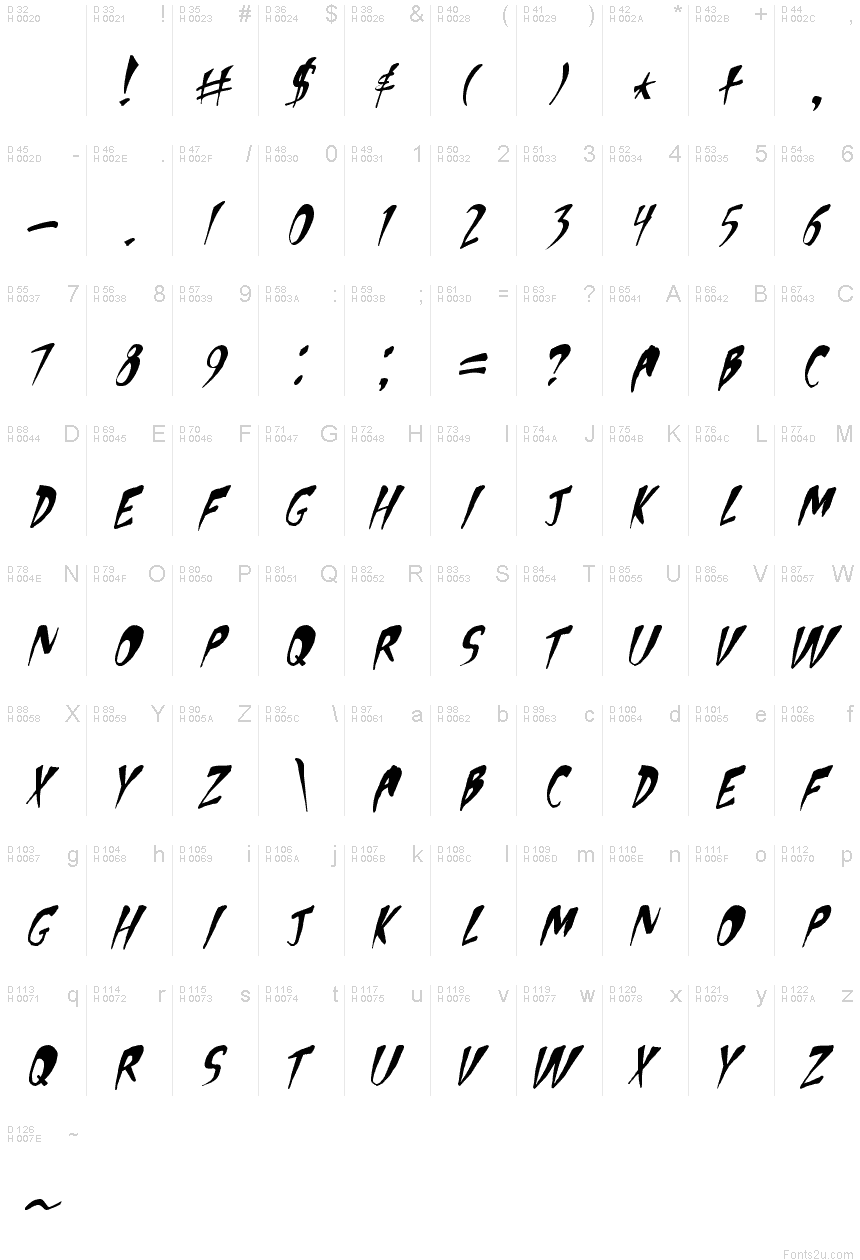
Apocalypse 1 autorstwa Roba Dobi to darmowy, przerażający krój displayowy, który wygląda, jakby został wyryty na stronie ociekającym farbą pędzlem. Litery pochylają się do przodu w gorączkowym skosie, a ich krawędzie rozpadają się na ostre, poszarpane kształty, które budzą niepokój i poczucie niestabilności. Nierówne pociągnięcia i atramentowe tekstury nadają rodzinie Apocalypse surową, apokaliptyczną energię, która natychmiast buduje napiętą, chaotyczną atmosferę.
Dzięki Apocalypse 1 nagłówki uderzają jak sceny z horroru, więc font ten świetnie sprawdza się na plakatach filmów grozy, ulotkach na Halloween, okładkach albumów metalowych lub punkowych, tytułach gier, identyfikacji wizualnej domów strachów oraz okładkach thrillerów. Ten darmowy font najlepiej prezentuje się w dużym rozmiarze, pozwalając, by to jego poszarpana sylwetka grała główną rolę. Zestaw go z małym, czytelnym krojem bezszeryfowym w tekstach towarzyszących, aby zachować przejrzystość układu, podczas gdy krój Apocalypse 1 zajmie się budowaniem klimatu grozy.